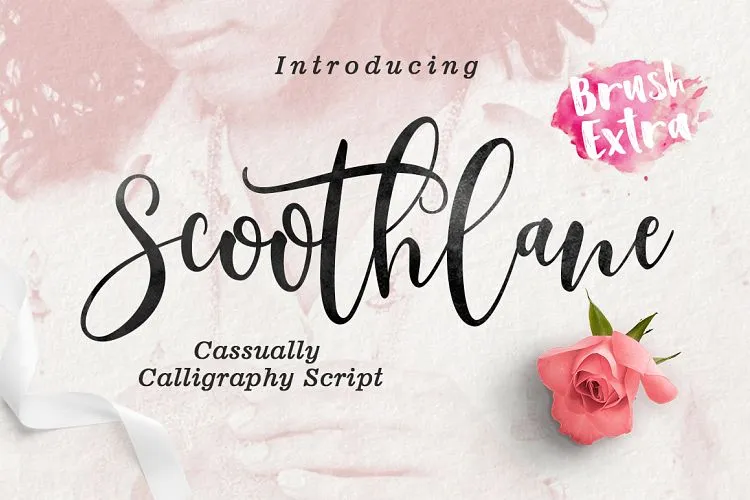
Scoothlane Script Font – Download Grátis
Olha aqui uma nova fonte chamada Scoothlane Script Font para você explorar! Especialmente projetada pelo designer zziplex, esta é uma fonte script com estilo de escreveraio elegante e facil de usar sem perder tempo. O resultado? Uma fonte que ajuda a criar trabalhos incríveis sem esforço. Introduzimos Scoothlane Script Font em nossa coleção de fonts, criada e compartilhada pelo designer MERCURIAL. Com suas letras suaves e linhas divertidas, esta font é um verdadeiro toque único, cheia de alegria e paixão. E complementando tudo isso, o Scoothlane Script Font inclui uma letra com pincel que certamente fará você se sentir entusiasmado para incorporar em suas criações únicas. Scoothlane Script Font é ideal para aqueles que buscam um toque diferenciado e sofisticado nas suas obras de arte digitais. Seja para desenhos de animações, letras de músicas ou até mesmo gráficos de design editorial, esta fonte irá transformar qualquer projeto em algo singular e especial. Acesse nosso catálogo para explorar este novo lançamento da zziplex – Scoothlane Script Font!